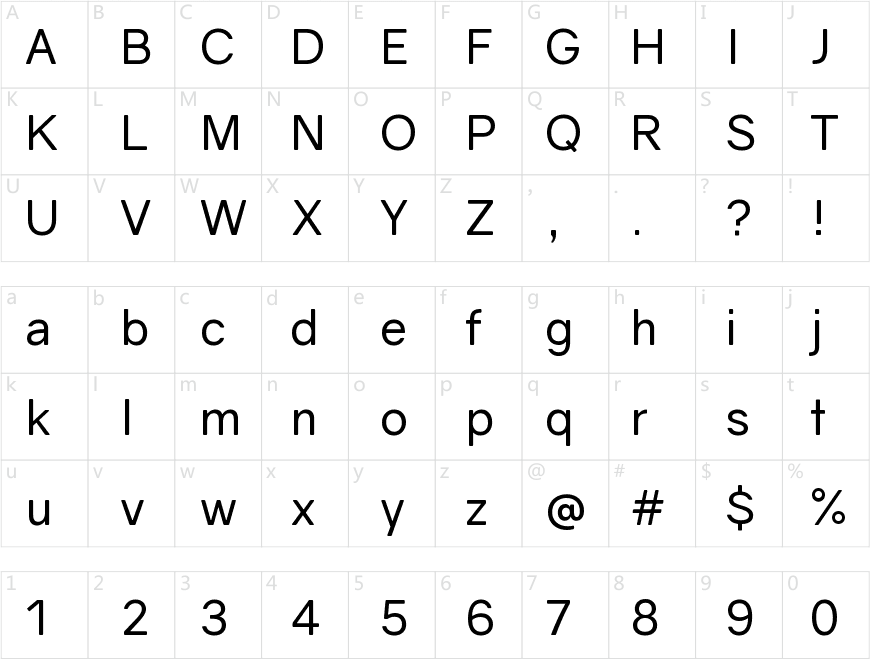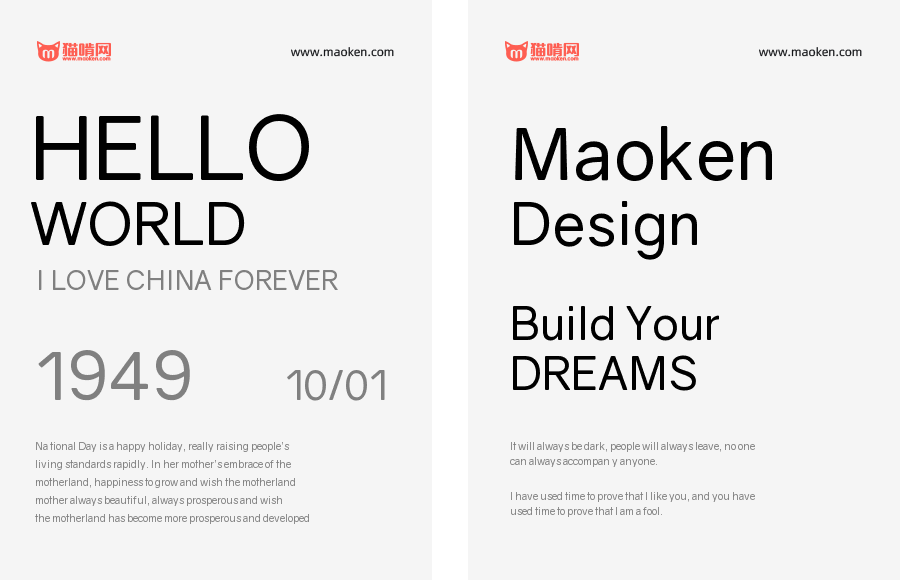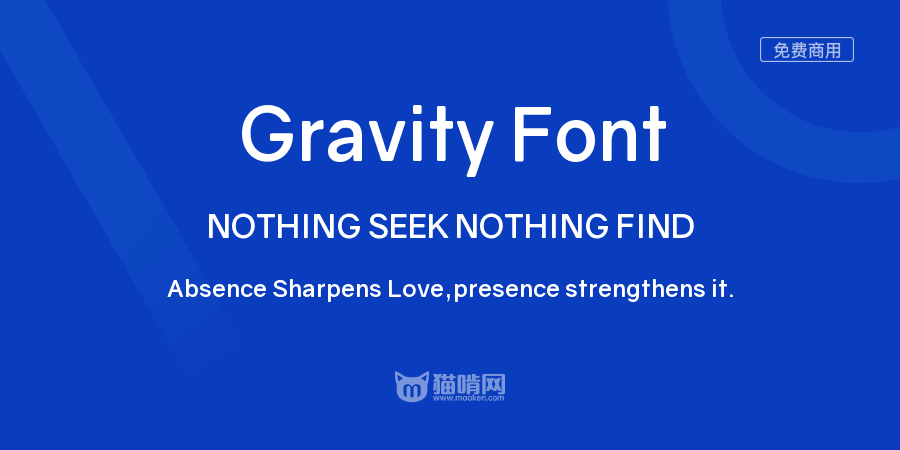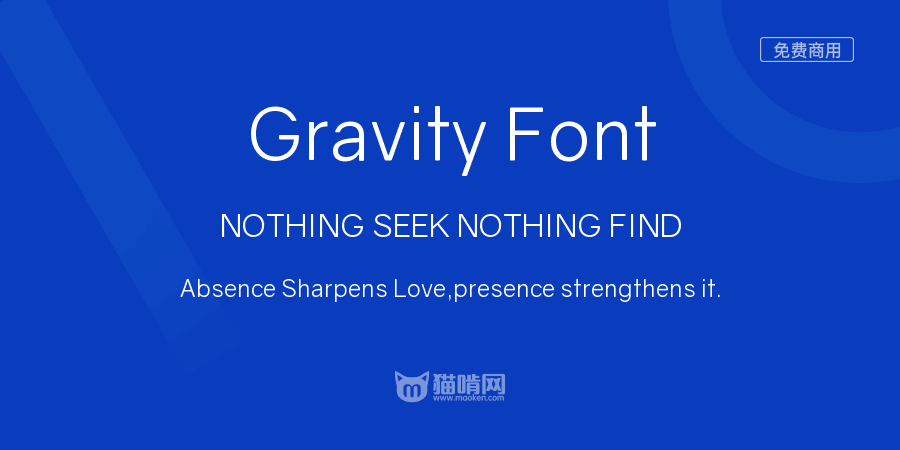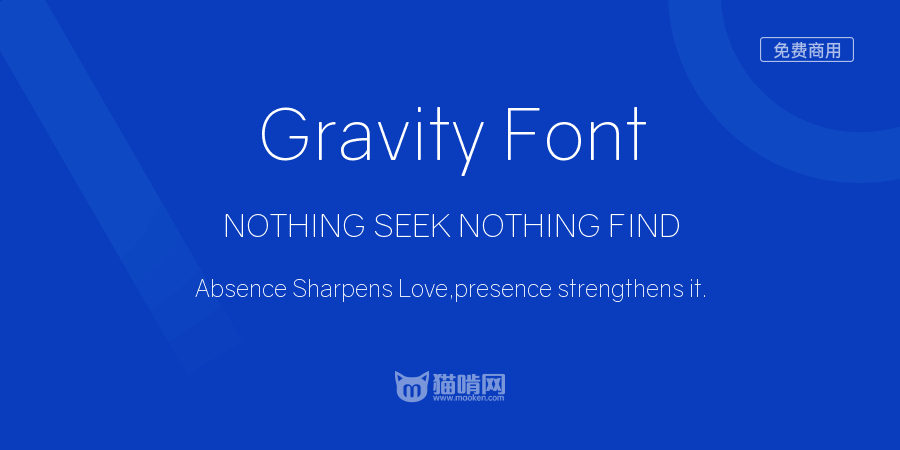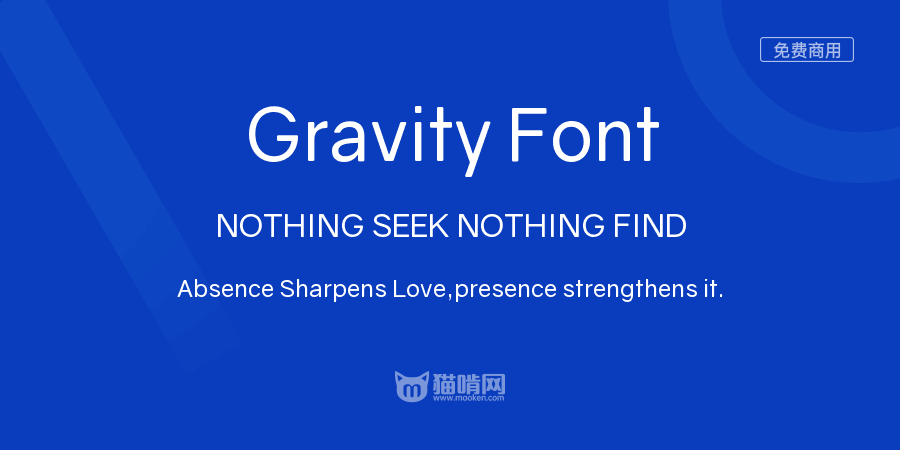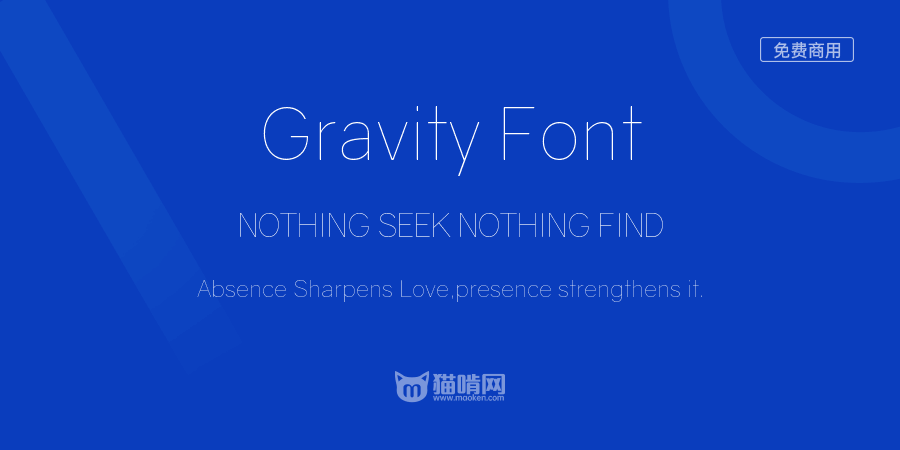
Gravity Font
字体作者:Vincenzo Vuono (外国) 字体字重:5个
Gravity是一个排版实验,源于加深我对这门学科知识的渴望,字体使用“重力”作为字体的独特、功能和美学特征。
Gravity也是一种新的几何无衬线字体设计与平衡和大计数器。由“Accademia di Belle Arti Palermo”用作官方字体。